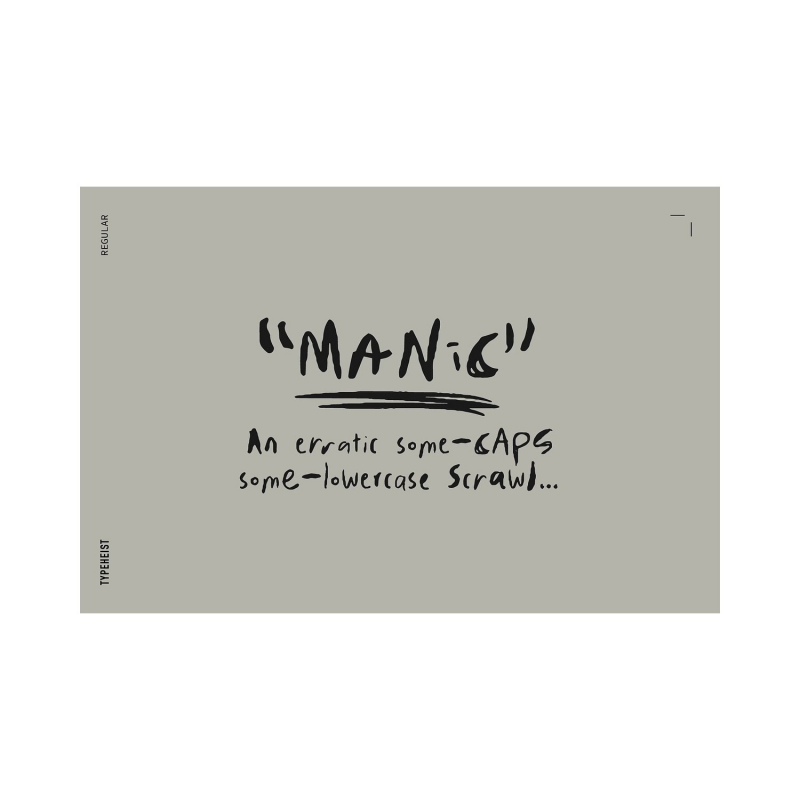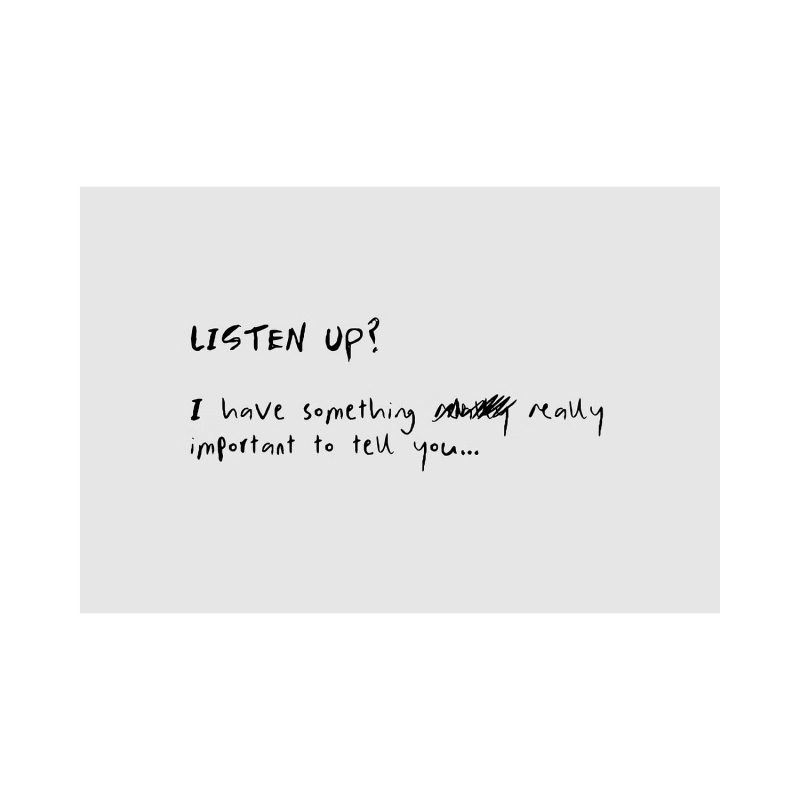
ما يحتويه::مانيك العادية (بما في ذلك جميع الحروف الرسومية البديلة)
نمط الخط:سان شريف
وصف
غير منتظم بعض الأحرف الكبيرة بعض الأحرف الصغيرة الكتابة... ويعرف أيضا باسم خط اليد. فوضوي وواقعي. مرسومة باليد وتحويلها إلى خط لجميع احتياجات الطباعة الهوسية الخاصة بك.
تعني ثلاثة أنماط خطوط "بديلة" أن هناك ما مجموعه أربعة أشكال مختلفة لكل حرف ورقم من الألف إلى الياء ، حيث ينتج كل نمط خط فردي مظهرا عاما مختلفا قليلا (ولكن دائما مهووسا).
يحتوي Manic على 100+ حروف مركبة بما في ذلك مجموعات الأحرف المزدوجة لكل من الأحرف الكبيرة والصغيرة ، بحيث يمكنك جعل كل ما تقوم بإنشائه بريا وفريدا حسب حاجتك ;)